Khi thiết kế bằng tiếng Việt, font chữ không chỉ cần đẹp mà còn phải rõ ràng, ổn dấu và phù hợp với đúng tinh thần ngành hàng. Với chủ đề mỹ phẩm, font ảnh hưởng trực tiếp đến cảm nhận về thương hiệu, độ cao cấp của sản phẩm và tính chuyên nghiệp của toàn bộ ấn phẩm.
Bài viết này dành cho designer trong lĩnh vực beauty, chủ shop skincare, spa bán mỹ phẩm và các thương hiệu cosmetics đang cần chọn font phù hợp cho poster skincare, banner mỹ phẩm, bao bì và social post. Đồng thời, đây cũng là bộ gợi ý font riêng trên S99.vn để bạn dễ tham khảo và hạn chế trùng lặp với những bài font khác.
Nhu cầu tìm font chữ mỹ phẩm thường bắt đầu từ một bài toán rất thực tế: cần một kiểu chữ vừa đẹp trên preview, vừa dùng ổn khi đặt vào layout thật. Nhiều font nhìn bắt mắt khi đứng riêng, nhưng khi đưa lên poster, banner, bao bì hoặc social post lại không còn giữ được sự tinh tế như mong muốn.
Với thiết kế tiếng Việt, yếu tố Việt hóa đặc biệt quan trọng. Những dấu như sắc, huyền, hỏi, ngã, nặng, mũ hay móc nếu đặt lệch, chạm nhau hoặc mất cân đối sẽ làm tổng thể thiết kế kém sang và thiếu chuyên nghiệp. Vì vậy, trước khi chốt font cho một dự án mỹ phẩm, bạn nên gõ thử ngay tiêu đề, slogan hoặc tên sản phẩm thực tế để kiểm tra khả năng hiển thị.
Tiêu chí chọn font chữ mỹ phẩm đẹp và dễ dùng
1. Đúng cảm xúc ngành hàng
Mỗi font đều tạo ra một cảm giác thương hiệu khác nhau. Với ngành mỹ phẩm, đặc biệt là skincare, ưu tiên thường là thanh lịch, sạch, cao cấp và tinh tế. Một font phù hợp sẽ giúp sản phẩm trông chỉn chu hơn ngay từ cái nhìn đầu tiên.
2. Đọc rõ ở nhiều kích thước
Font dùng cho mỹ phẩm không chỉ xuất hiện ở tiêu đề lớn mà còn đi vào các phần như nhãn phụ, giá bán, mô tả ngắn hoặc social post trên điện thoại. Vì vậy, bạn nên kiểm tra font ở cả kích thước lớn lẫn nhỏ để chắc chắn rằng chữ vẫn rõ và không bị rối.
3. Dấu tiếng Việt phải gọn và cân đối
Đây là tiêu chí gần như bắt buộc. Một font có dấu tiếng Việt đẹp sẽ giúp headline trông sang hơn, thông tin bán hàng rõ hơn và tổng thể thiết kế giữ được sự tinh tế. Ngược lại, font có dấu lệch hoặc chạm chữ rất dễ làm hỏng cảm giác cao cấp của ngành mỹ phẩm.
4. Dễ phối với font phụ
Một layout đẹp thường không chỉ dùng một font duy nhất. Bạn nên chọn một font chính để tạo cá tính cho tiêu đề và một font phụ để đảm bảo phần mô tả, thành phần, công dụng, giá hoặc CTA dễ đọc. Font mỹ phẩm đẹp là font có thể phối tốt trong một hệ thống chữ chứ không chỉ đẹp khi đứng riêng.
5. Dùng được trên nhiều định dạng
Font phù hợp cho ngành mỹ phẩm nên hoạt động tốt trên poster, banner, bao bì, website và social post. Điều quan trọng không chỉ là làm headline nổi bật mà còn giúp sản phẩm trông đáng tin, đồng bộ và chuyên nghiệp ở nhiều điểm chạm khác nhau.
Dưới đây là bộ font riêng cho bài viết này, được chọn theo hướng thanh lịch, cao cấp, sạch và phù hợp với ngành beauty. Bạn nên tải khoảng 3 đến 5 font gần nhất với phong cách thương hiệu của mình, sau đó thử trực tiếp trên layout thật để chọn ra bộ phù hợp nhất.
Font TH Retalin Regular – sang trọng, hợp poster mỹ phẩm và thiết kế beauty cao cấp.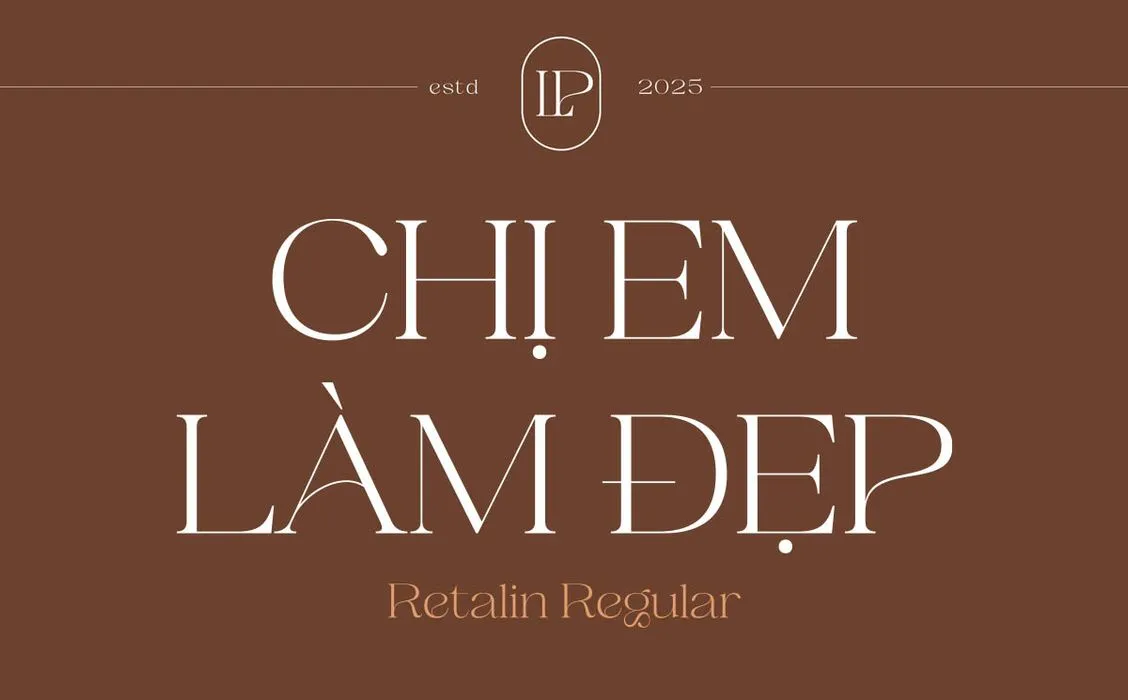
Font TH Wrigskan – serif cao cấp, phù hợp với serum, skincare premium và các sản phẩm dưỡng da thiên về cảm giác sang trọng.
Font iCiel Mijas Việt hóa – mềm mại, thanh lịch, phù hợp với nhãn mỹ phẩm nhẹ nhàng và các layout nữ tính.
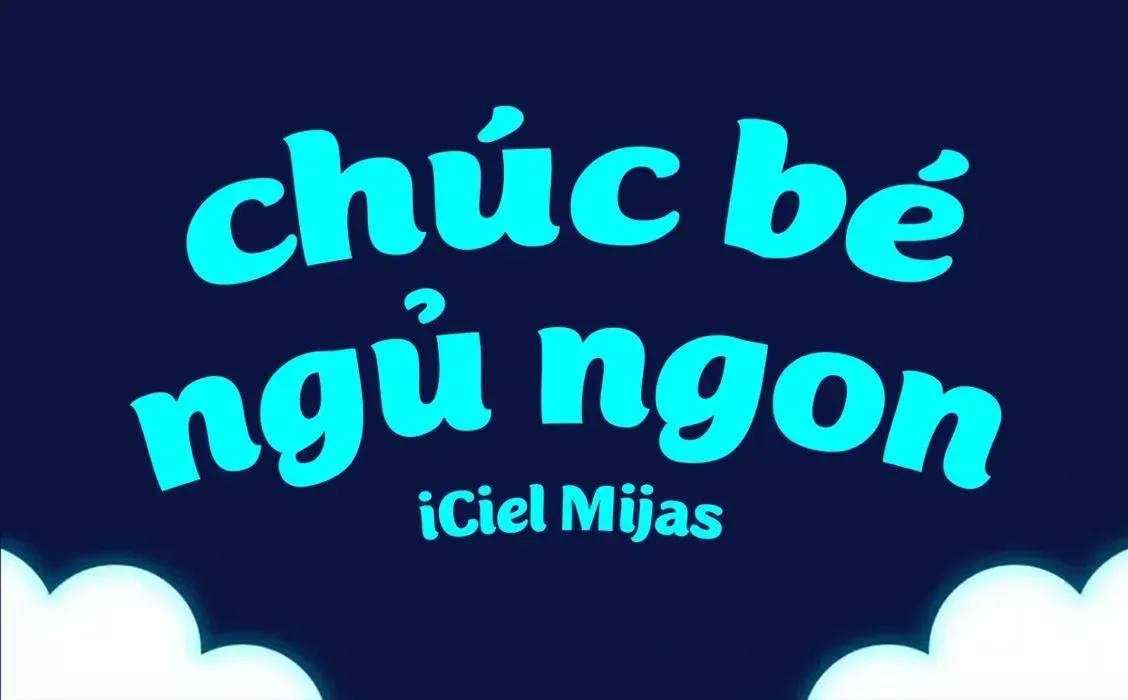
Font TH Saviera - Tải về
Font TH Saviera – hiện đại, sạch và tối giản, phù hợp với các thương hiệu skincare theo hướng tinh gọn.
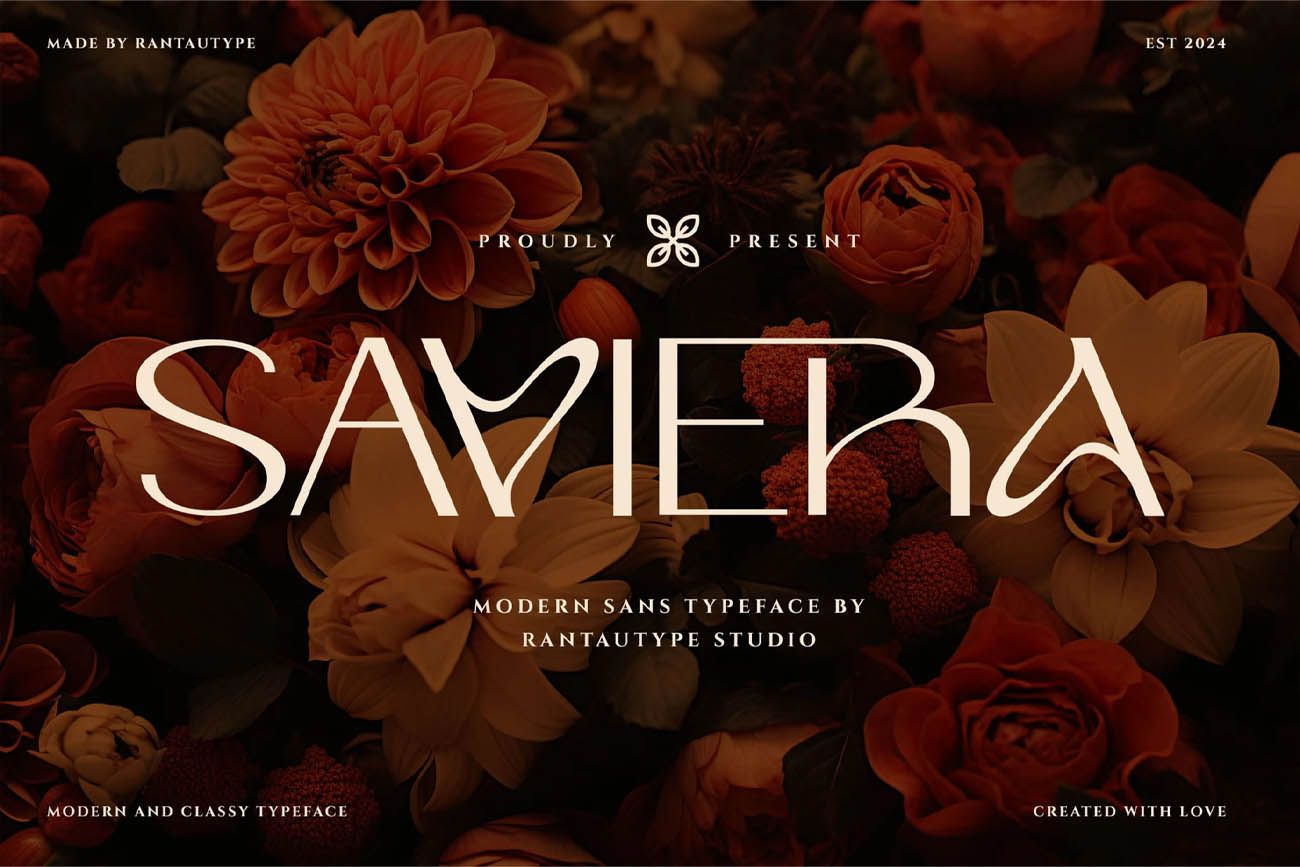
Font TH Top Luxury - Tải về
Font TH Top Luxury – sans-serif sang trọng, hợp với thương hiệu beauty cao cấp và thiết kế poster cần cảm giác premium.
Font TH Manisans - Tải về
Font TH Manisans – có nhiều style, phù hợp để phát triển cả bộ nhận diện mỹ phẩm từ tiêu đề đến nội dung phụ.
Font TH Artega - Tải về
Font TH Artega – gọn gàng, thương hiệu và dễ dùng cho bao bì, website hoặc social post mỹ phẩm.
Khi chọn trong danh sách trên, bạn nên tải 3-5 font gần nhất với phong cách thương hiệu rồi thử trực tiếp trên layout thật. Đừng chỉ nhìn preview riêng lẻ, vì font chỉ bộc lộ đúng giá trị khi đặt cùng ảnh, màu sắc, CTA và nội dung thật.Khi chọn trong danh sách này, đừng chỉ nhìn preview font riêng lẻ. Hãy thử đặt font lên ảnh sản phẩm thật, nền màu thật, câu CTA thật và các dòng thông tin thực tế. Chỉ khi nằm trong bố cục hoàn chỉnh, font mới bộc lộ đúng giá trị của nó.
Ứng dụng font mỹ phẩm trong thiết kế thực tế
Font mỹ phẩm có thể dùng cho rất nhiều hạng mục như headline chính, tiêu đề phụ, poster skincare, banner mỹ phẩm, social post beauty, website, catalog, nhãn dán và bao bì sản phẩm. Tuy nhiên, ở mỗi nền tảng, cách dùng font cần được điều chỉnh cho phù hợp.
Với poster hoặc banner, bạn nên dùng font mạnh nhất cho thông điệp chính để tạo điểm nhấn thị giác.
Kết luận
Một bộ font chữ mỹ phẩm tốt không chỉ giúp thiết kế đẹp hơn mà còn giúp thương hiệu nhất quán, dễ đọc và đúng cảm xúc hơn. Với ngành skincare và cosmetics, font cần hội tụ đủ ba yếu tố: thanh lịch, chuyên nghiệp và ổn dấu tiếng Việt. Trước khi chốt dùng cho dự án chính thức, hãy luôn thử font trên layout thật để chắc chắn rằng nó phù hợp với hình ảnh thương hiệu và mục tiêu truyền thông của bạn.